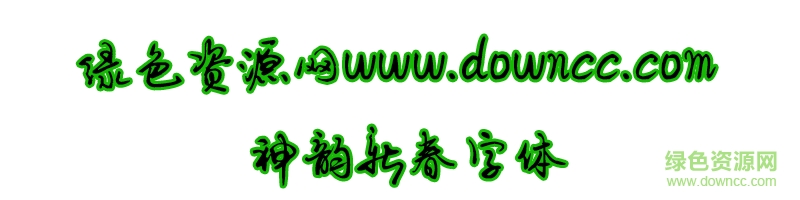
神韻新春體字體是一款神韻字體,在使用的過(guò)程中將獲得不錯(cuò)的視覺(jué)享受,當(dāng)你在使用字體進(jìn)行各項(xiàng)工作的時(shí)候也能夠感受到優(yōu)質(zhì)的字體樣式所帶來(lái)的舒適體驗(yàn),快來(lái)綠色資源網(wǎng)下載吧!
神韻新春體讓人看上去十分好看,在藝術(shù)字編輯中文字編輯中讓我覺(jué)得十分享受!